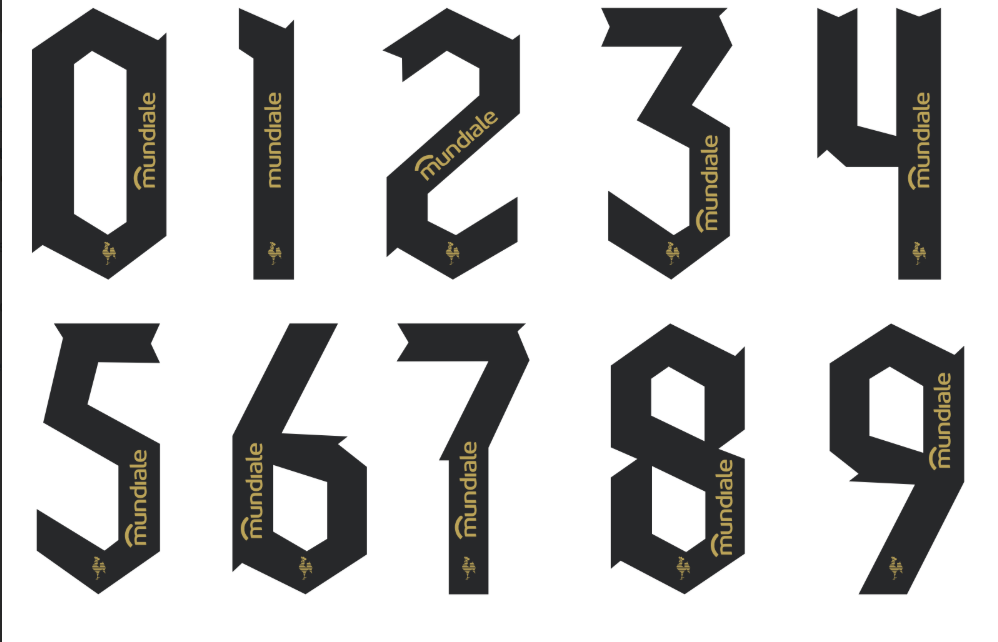
A paixão pelo Galo vai além das quatro linhas; ela está em cada detalhe do “Manto da Massa”. Para a temporada 2025, o Atlético Mineiro apresenta uma identidade visual renovada em seus uniformes, e a tipografia usada nos nomes e números dos jogadores é uma parte fundamental dessa evolução.
Seja para os uniformes desenvolvidos pela Adidas ou para as edições especiais do Manto, a fonte de 2025 foi criada para ser moderna, legível e carregar o DNA de raça e vitória do clube. Agora, você pode ter essa fonte exclusiva para usar em seus projetos pessoais, artes e mockups.
- Nome da Fonte: Atlético Mineiro 2025
Estilo Visual e Design
A tipografia do Atlético Mineiro para 2025 combina força e modernidade. Ela possui traços robustos e cantos levemente chanfrados (cortados), que dão uma sensação de dinamismo e velocidade.
É um design proprietário que se destaca pela clareza, garantindo excelente legibilidade tanto na TV quanto no estádio. Diferente de fontes genéricas, ela foi pensada para refletir a energia da torcida e a identidade “Vingador” do Galo, sendo usada em todo o enxoval do clube, desde o time profissional masculino e feminino até as categorias de base.